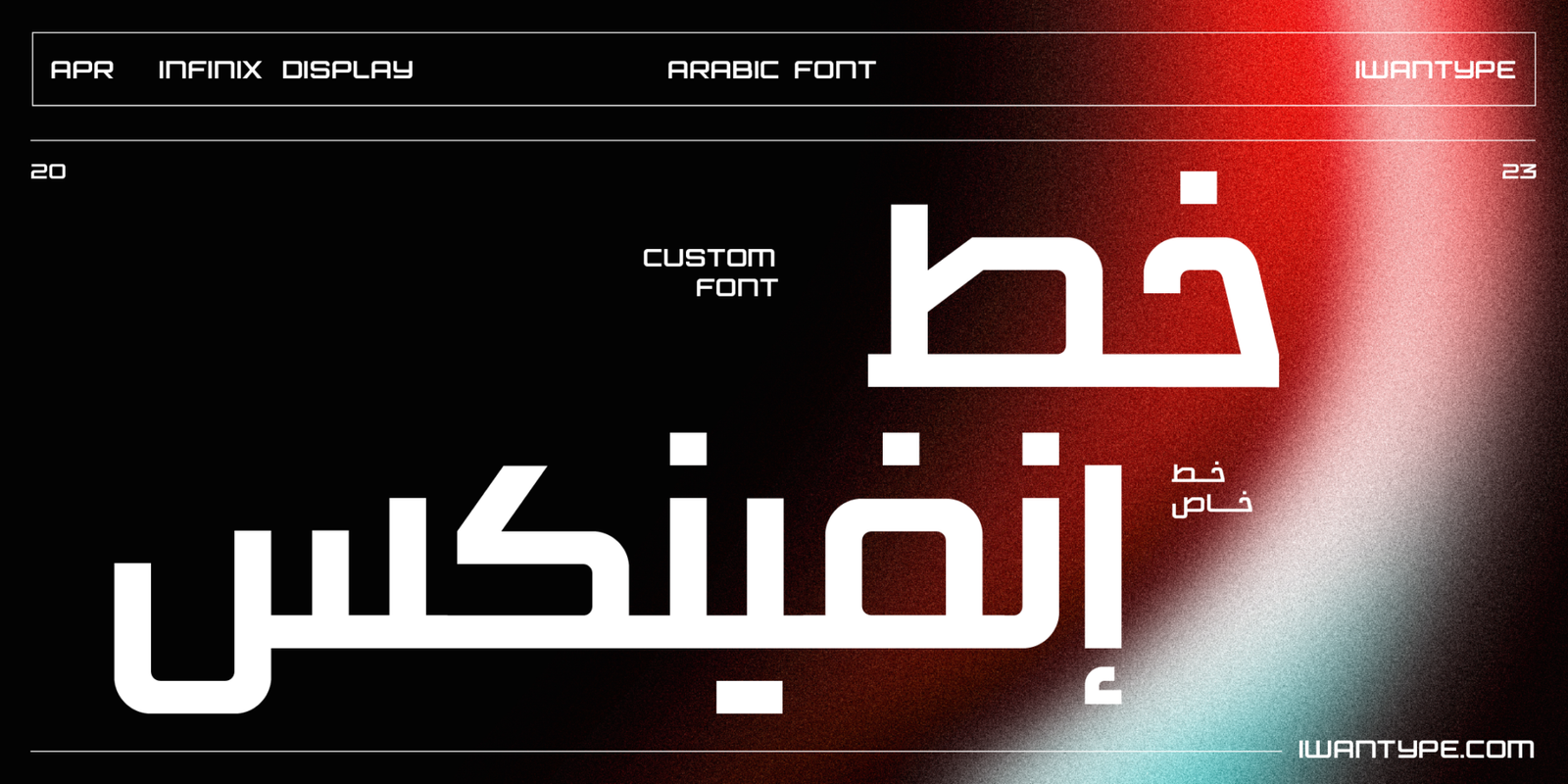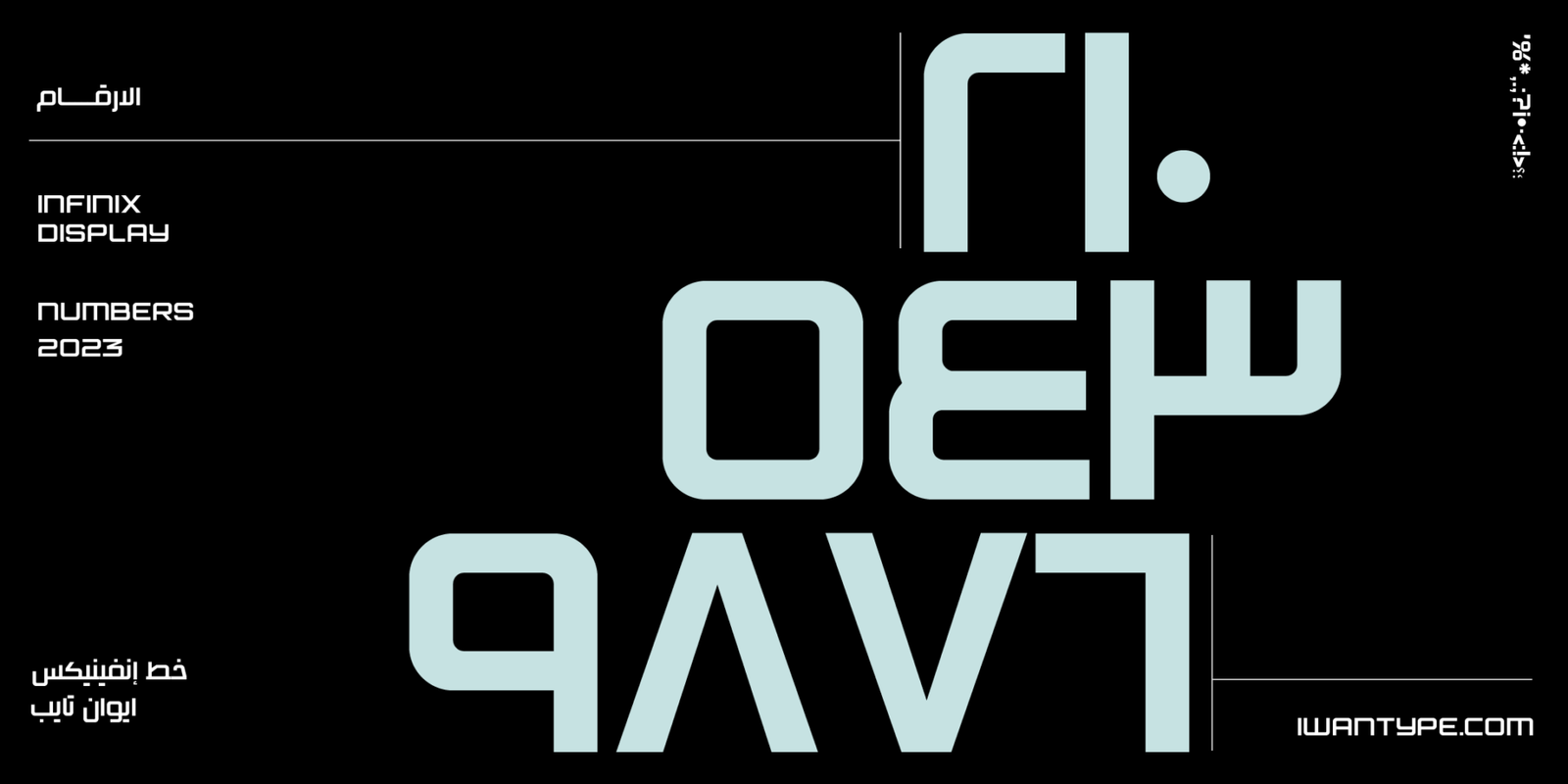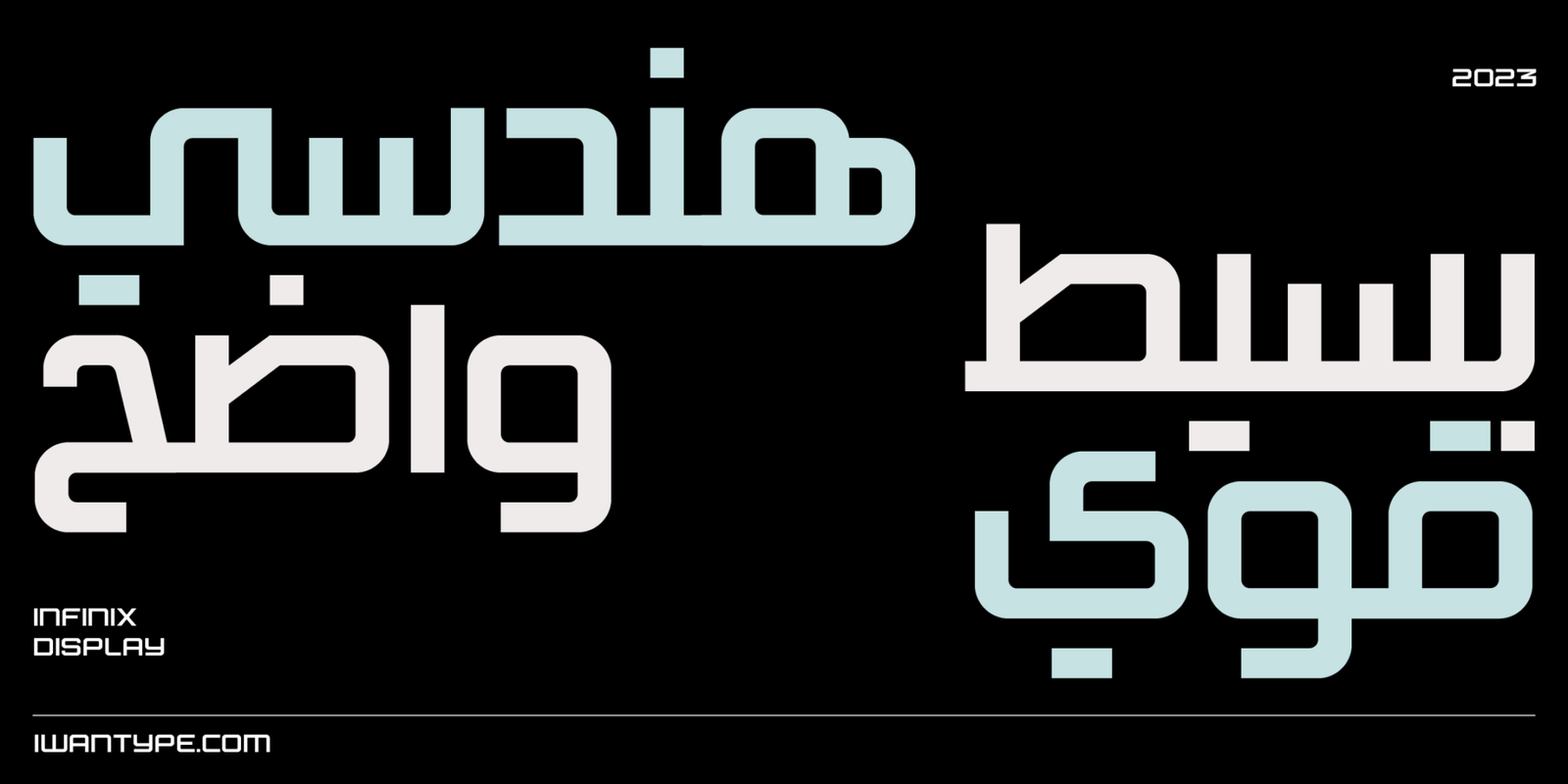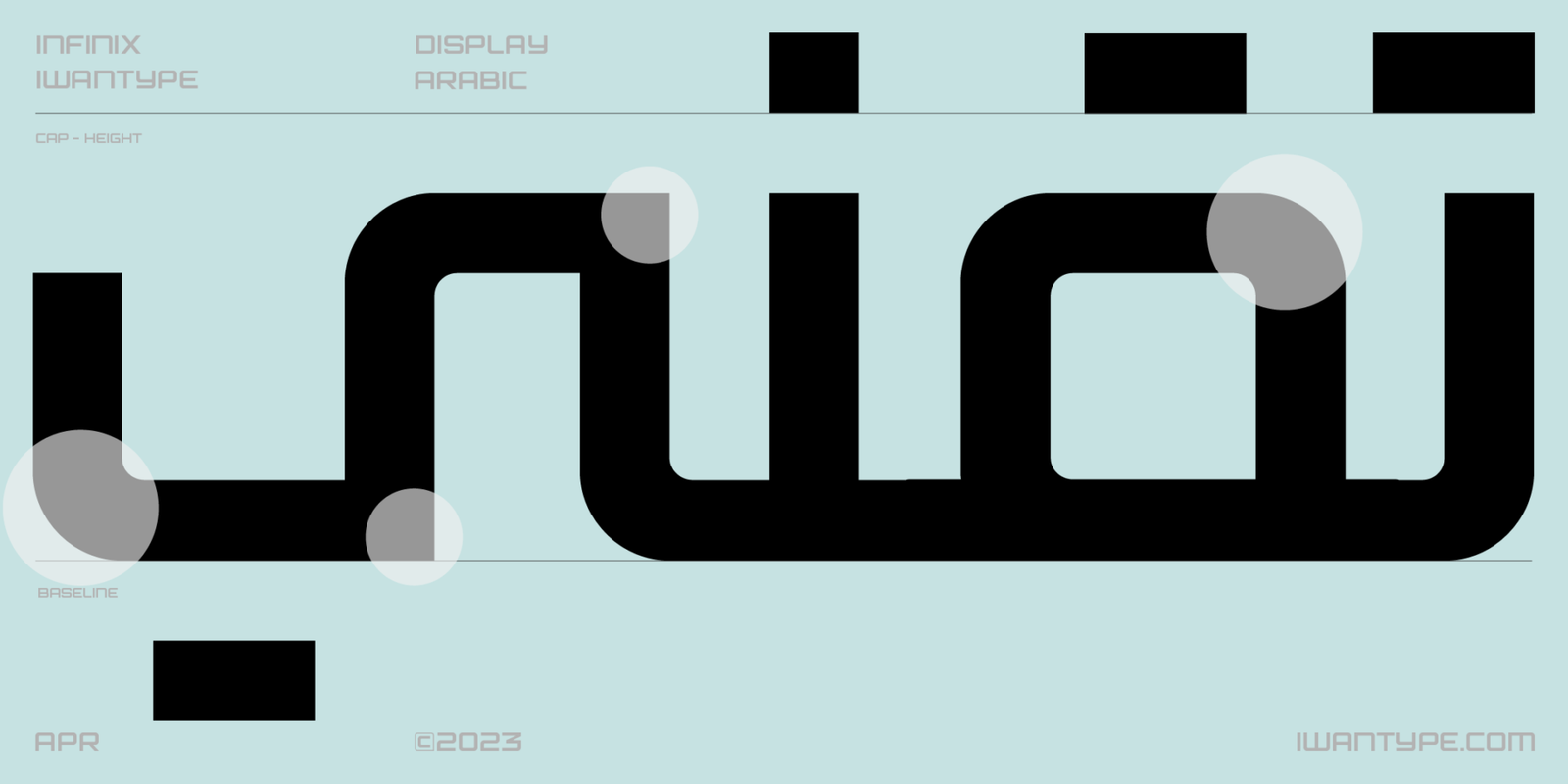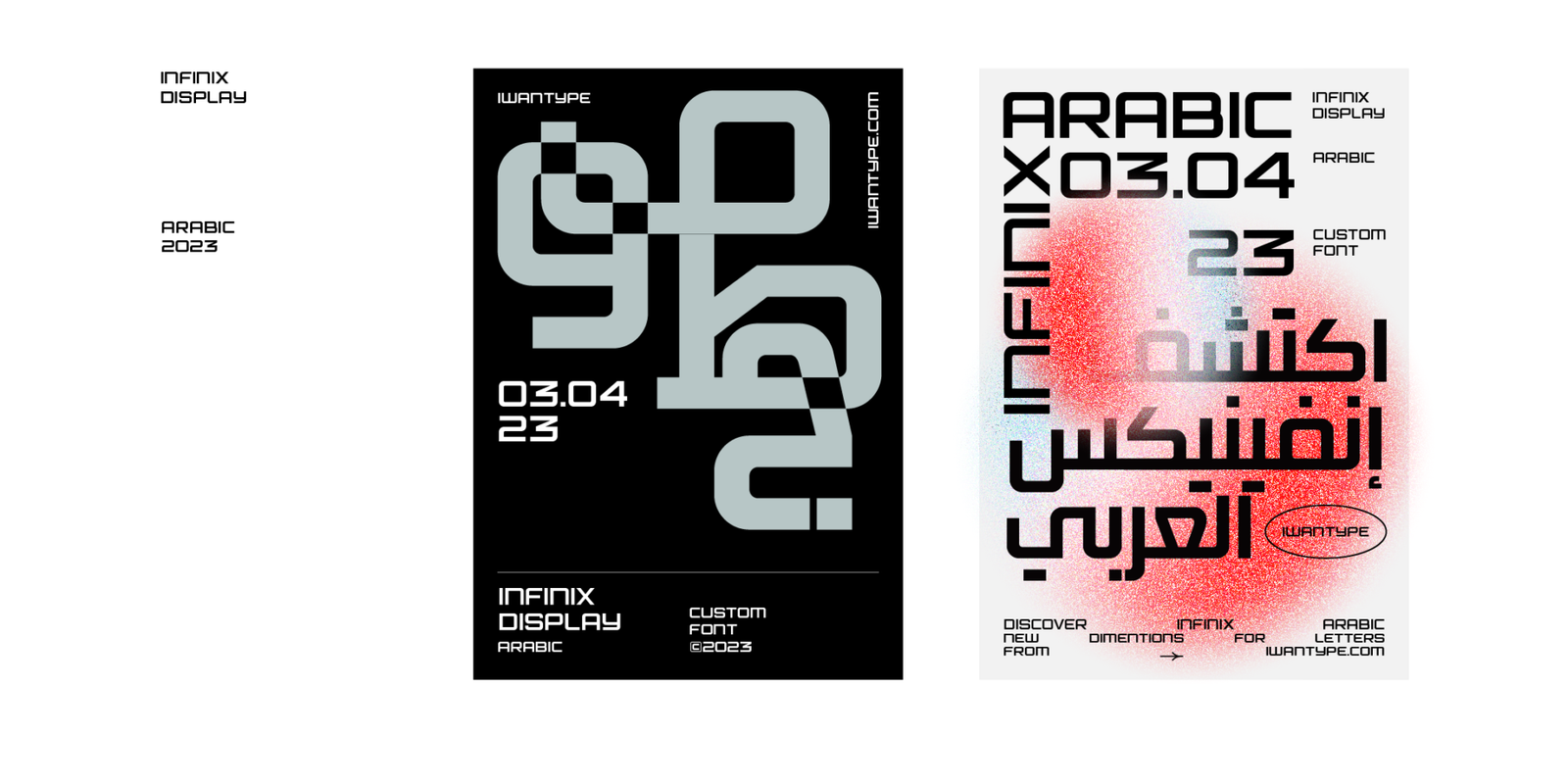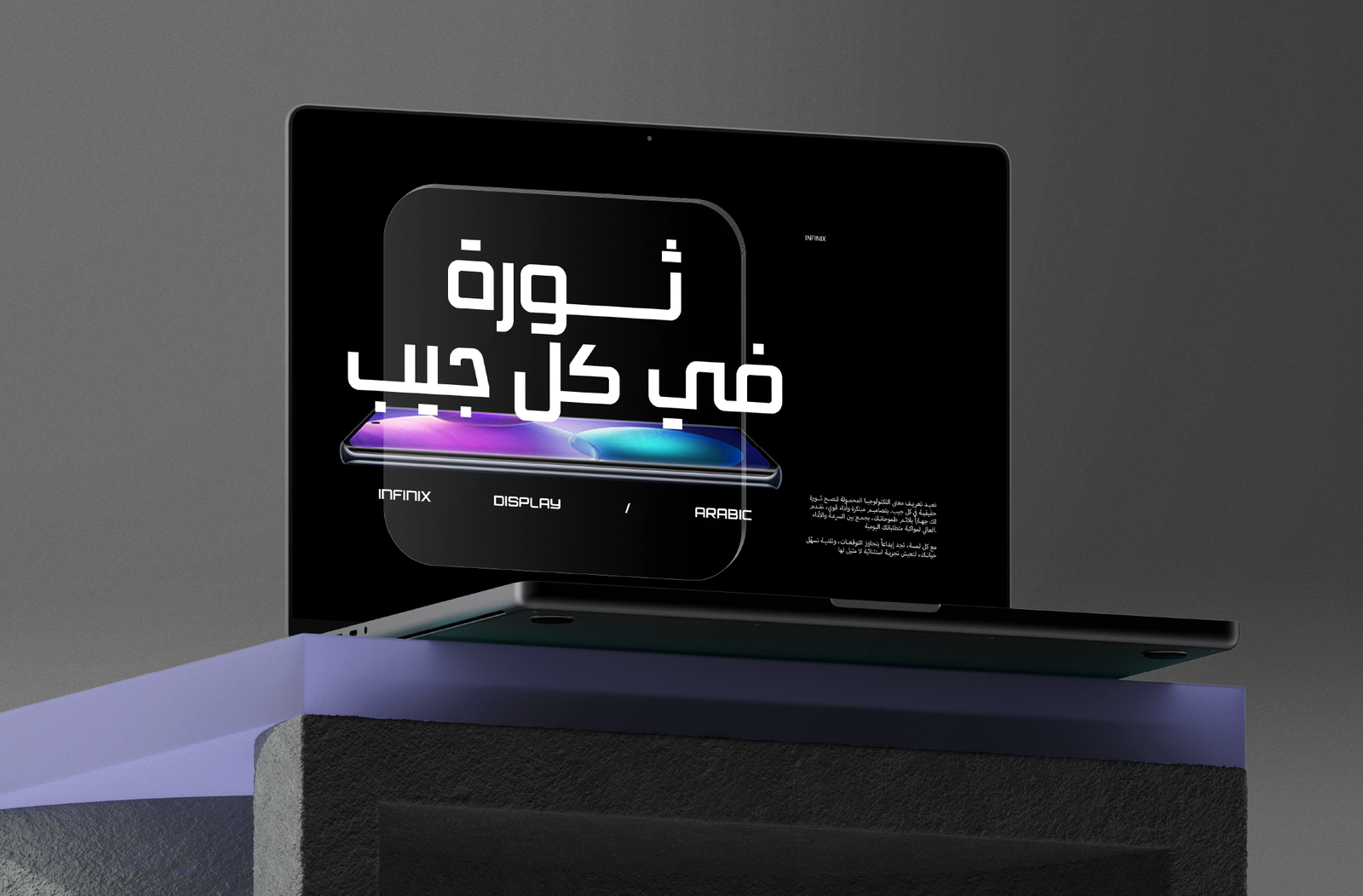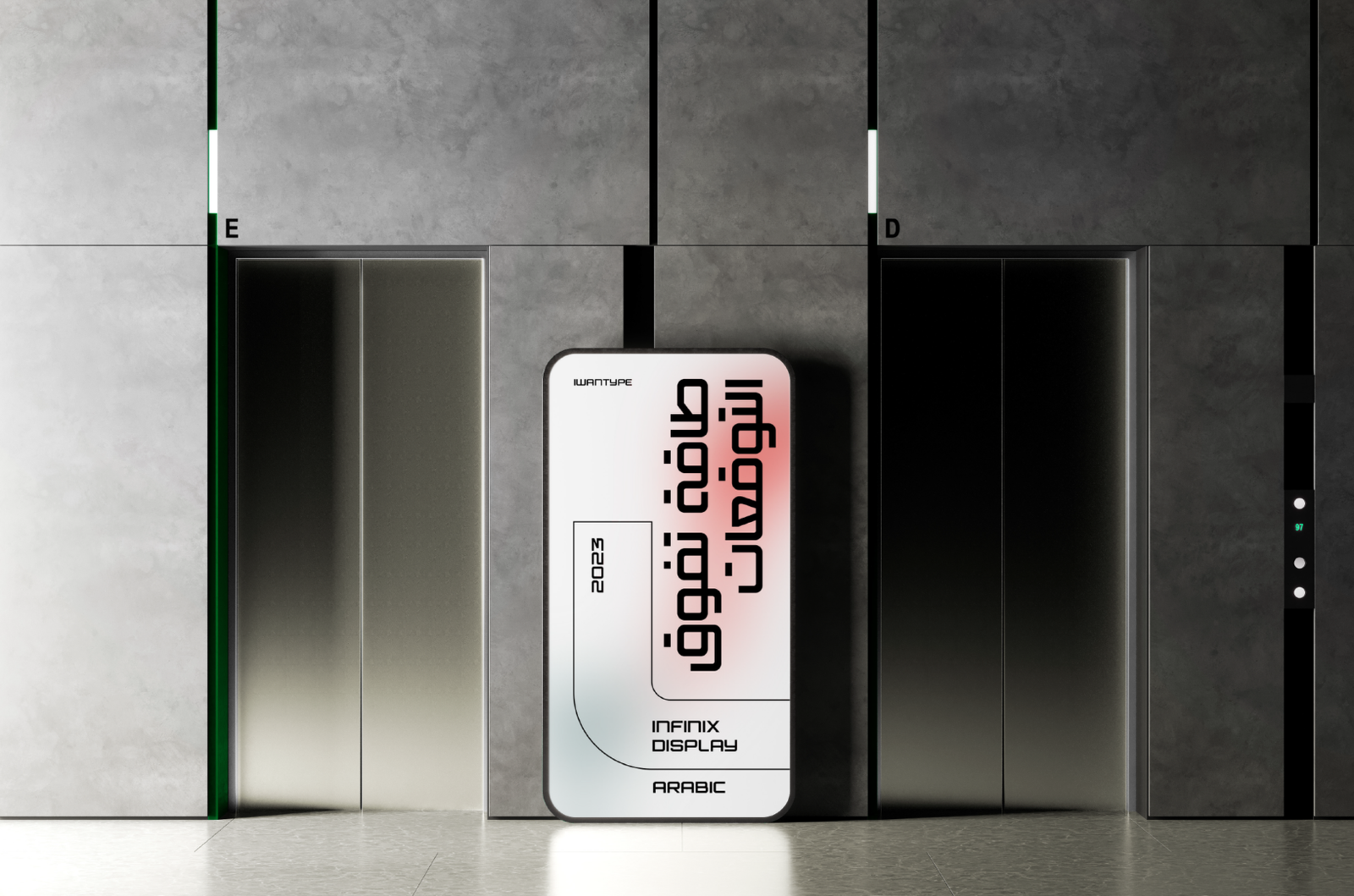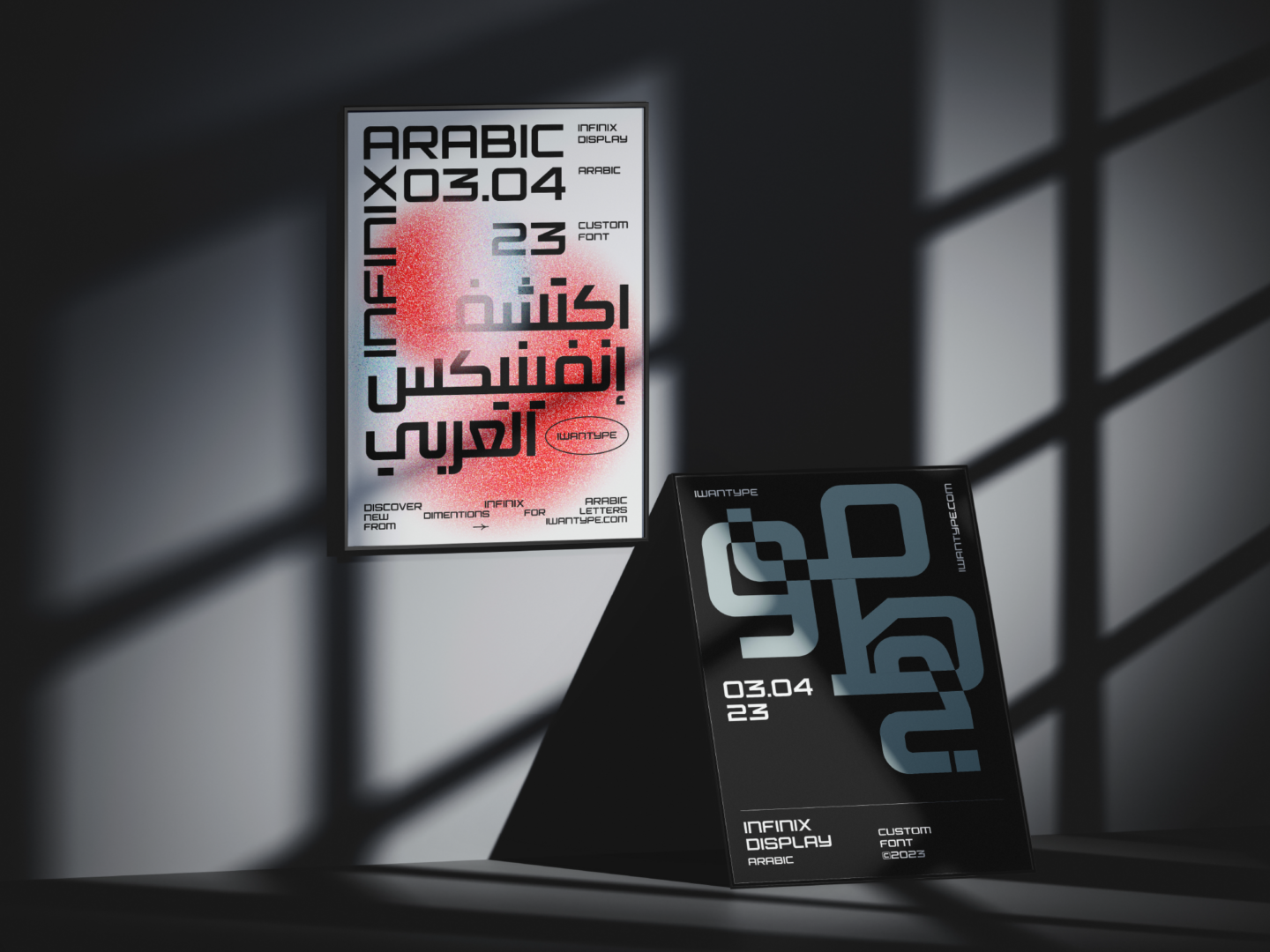
خط إنفينكس للعناوين – خط طباعي خاص
تم تكليفنا بتصميم النسخة العربية من خط Infinix Display بالتعاون مع Mubien Brands. تم تطوير النسخة العربية بأسلوب حديث وجيومتري، بحيث تتناغم مع سمات النسخة اللاتينية وتكمل طابع العلامة التجارية. يمتاز الخط بخطوط حادة وجريئة، مما يعكس التركيز على الدقة والكفاءة، ويتماشى مع الهوية البصرية التي تعبر عن التكنولوجيا المتقدمة لشركة Infinix.
Agency: Mubien Brands
Account Management: Victor Mubien
Creative Direction: David Mubien, Younes Badi, Neko Zhang
Brand Manager: Yini Zhao
Type Design: Daniel Iglesias
Languages Adaptation: Sol Matas, Ahmed Zaza, Deltatype
Art Direction: Daniel Iglesias, Yini Zhao, Carlos Almagro
UX/UI: Javier Ochoa, Patricia Orden
Video Production Manager: Vincent Bao
Head of Marketing: Lake Hu